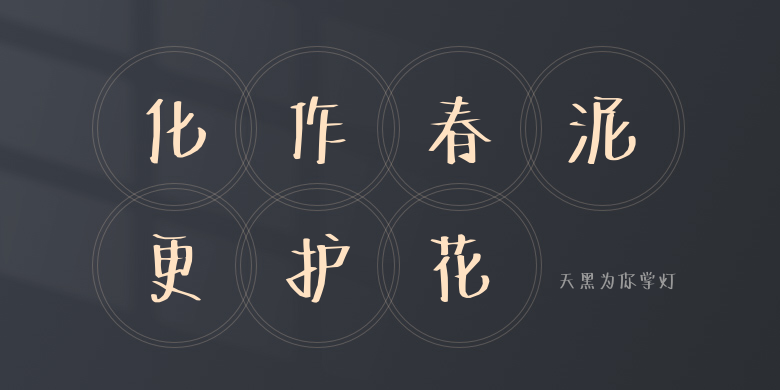
天黑为你掌灯
天黑为你掌灯,这款字体结构工整、笔画清晰,兼顾美观与易读性,适用于标题、正文、海报、包装、LOGO 等多种场景。字形优雅稳定,风格百搭耐看,适配日常排版与创意设计,让文字呈现更舒适、更具质感。天黑为你掌灯一笔一画,皆是细节,以均衡的比例、流畅的线条打造舒适视觉体验,字形端正大气,风格简约现代。无论是商业设计、品牌宣传还是日常排版,都能轻松驾驭,让文字更有格调与力量。天黑为你掌灯字体下载。